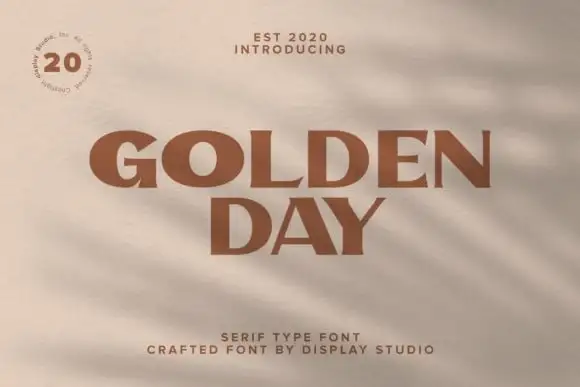
Golden Day Serif Font – Fonte Grátis
Golden Day Serif Font
A Golden Day Serif Font é uma fonte serif vintage que brilha com um ar retrô forte. Foi projetada para servir como base perfeita para nomes de marca personalizados e produtos complementares, com um gosto de aventura marinha. Inspirada na tipografia clássica, ela traz sua própria identidade única a qualquer projeto de design. Perfeita tanto para headlines de todos os tamanhos quanto para blocos de texto que possuem variáveis extremas, essa fonte serif se destaca em qualquer aplicação – seja web, impressão, ou mesmo gráficos em movimento. Golden Day será uma escolha perfeita para dar um toque especial a seu design.